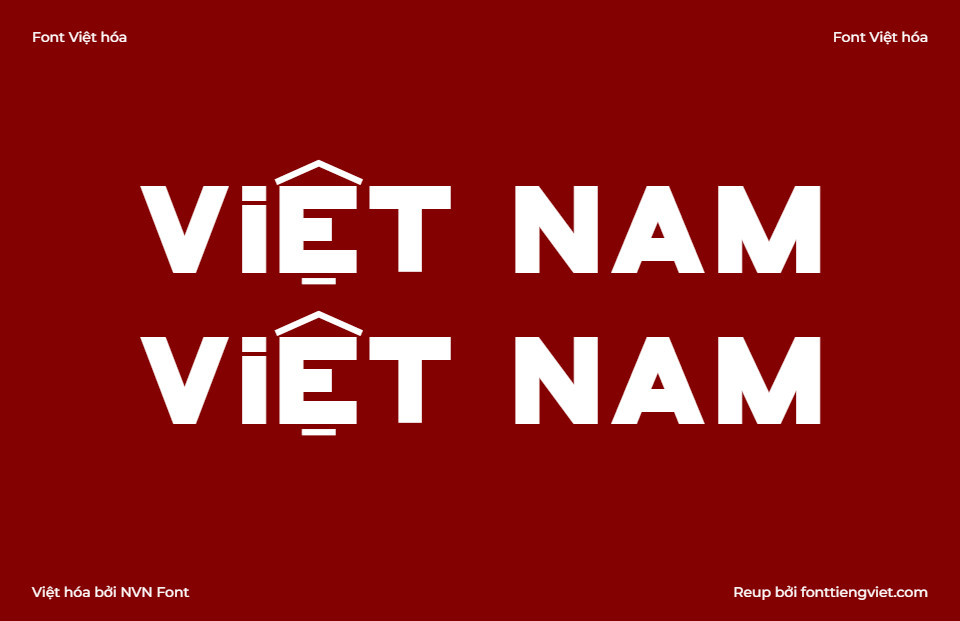
Font Việt hoá NVN VietNam Vintage Regular
Giới thiệu về Font Việt hoá NVN VietNam Vintage Regular
Trong thế giới thiết kế đồ họa hiện đại, việc tìm kiếm một bộ Font Miễn Phí mang đậm hơi thở hoài cổ nhưng vẫn đảm bảo tính ứng dụng cao là điều không hề dễ dàng. Font Việt hoá NVN VietNam Vintage Regular xuất hiện như một giải pháp hoàn hảo cho những ai yêu thích phong cách Retro và Vintage của Việt Nam thế kỷ trước. Bộ chữ này không chỉ đơn thuần là các ký tự mà còn là nhịp cầu nối liền quá khứ và hiện tại, mang lại cảm giác thân thuộc, mộc mạc và vô cùng tinh tế cho mọi bản thiết kế. Việc sử dụng font chữ này giúp các bạn học sinh và thầy cô giáo dễ dàng tạo ra những ấn phẩm truyền thông, báo tường hoặc bài giảng có sức hút thị giác mạnh mẽ, khơi gợi kỷ niệm về những bảng hiệu vẽ tay xưa cũ trên đường phố Sài Gòn hay Hà Nội.
Đặc điểm nổi bật của bộ Font Việt hoá NVN VietNam Vintage Regular
Thiết kế mang phong cách hoài cổ độc đáo
Điểm ấn tượng nhất của Font Việt hoá NVN VietNam Vintage Regular chính là những đường nét dày dặn, vững chãi nhưng không kém phần mềm mại ở các góc bo tròn. Kiểu dáng Regular giúp bộ font duy trì sự cân bằng, dễ đọc trên cả phương diện in ấn lẫn hiển thị kỹ thuật số. Các dấu tiếng Việt được trau chuốt tỉ mỉ, đảm bảo không bị lỗi font hay nhảy chữ khi soạn thảo nội dung dài. Đây là ưu điểm lớn giúp người dùng tiết kiệm thời gian chỉnh sửa và tập trung hoàn toàn vào ý tưởng sáng tạo.
Tính ứng dụng linh hoạt trong nhiều lĩnh vực
Dù bạn đang thiết kế một tấm poster cho sự kiện trường học, làm bìa sách hay tạo nội dung cho mạng xã hội, Font Việt hoá NVN VietNam Vintage Regular đều có thể đáp ứng tốt. Sự hoài cổ của nó cực kỳ phù hợp với các chủ đề về lịch sử, văn hóa, ẩm thực truyền thống hoặc các thương hiệu muốn xây dựng hình ảnh gần gũi với khách hàng. Trong môi trường giáo dục, thầy cô có thể dùng font này để làm tiêu đề cho các bài thuyết trình về văn học hoặc lịch sử Việt Nam, giúp học sinh cảm thấy hứng thú hơn với nội dung bài học thông qua giao diện trực quan sinh động.
Hướng dẫn sử dụng và tối ưu thiết kế với font chữ vintage
Cách phối hợp màu sắc hiệu quả
Để phát huy tối đa vẻ đẹp của Font Việt hoá NVN VietNam Vintage Regular, người dùng nên ưu tiên các bảng màu mang sắc thái trầm ấm như vàng nghệ, đỏ gạch, xanh rêu hoặc nâu đất. Những tông màu này khi kết hợp với đường nét của font chữ sẽ tạo nên một tổng thể hài hòa, đậm chất nghệ thuật cổ điển. Ngoài ra, việc thêm một chút hiệu ứng “noise” hoặc “texture” giấy cũ lên nền thiết kế cũng là một mẹo nhỏ để tăng thêm độ chân thực cho tác phẩm của bạn.
Lưu ý khi sử dụng trong văn bản
Mặc dù bộ chữ rất đẹp nhưng bạn nên sử dụng nó chủ yếu cho các phần tiêu đề, từ khóa quan trọng hoặc các đoạn văn ngắn để tránh gây mỏi mắt cho người xem. Đối với nội dung chi tiết, hãy kết hợp với các font chữ không chân (sans-serif) đơn giản để tạo sự tương phản cần thiết, giúp thông tin được truyền tải một cách mạch lạc và chuyên nghiệp nhất.
Kết luận về bộ Font Việt hoá NVN VietNam Vintage Regular
Có thể khẳng định rằng Font Việt hoá NVN VietNam Vintage Regular là một tài nguyên quý giá trong kho tàng font chữ Việt. Nó không chỉ đáp ứng yêu cầu về thẩm mỹ mà còn bảo tồn những giá trị văn hóa chữ viết truyền thống. Việc sở hữu bộ font này sẽ giúp các dự án cá nhân và học tập của bạn trở nên nổi bật và có bản sắc riêng. Hãy nhanh tay tải về và trải nghiệm sức hút từ Font Miễn Phí, Font Việt Hóa, Font Việt hoá NVN VietNam Vintage Regular để biến những ý tưởng trên trang giấy thành hiện thực sinh động ngay hôm nay.